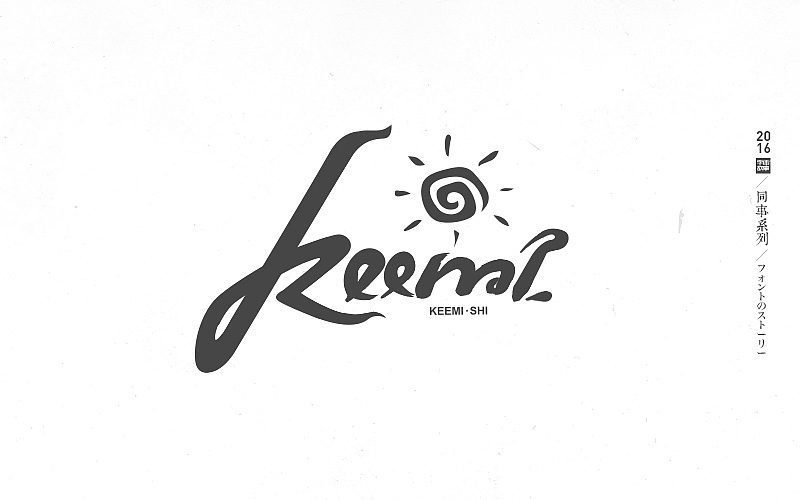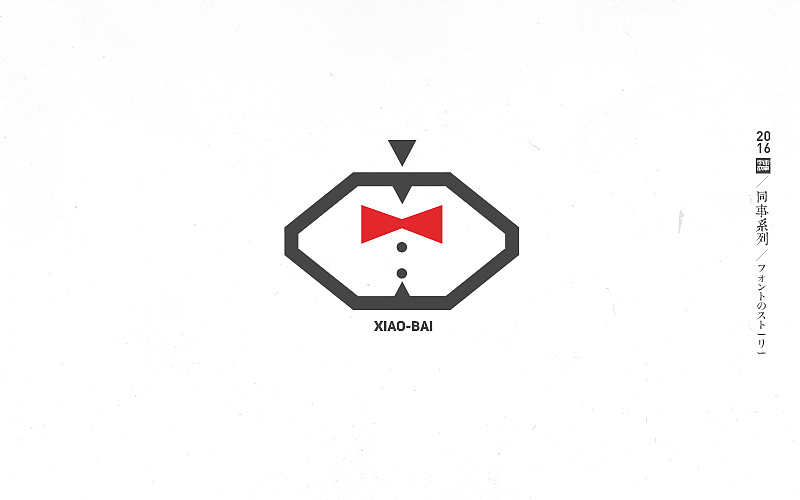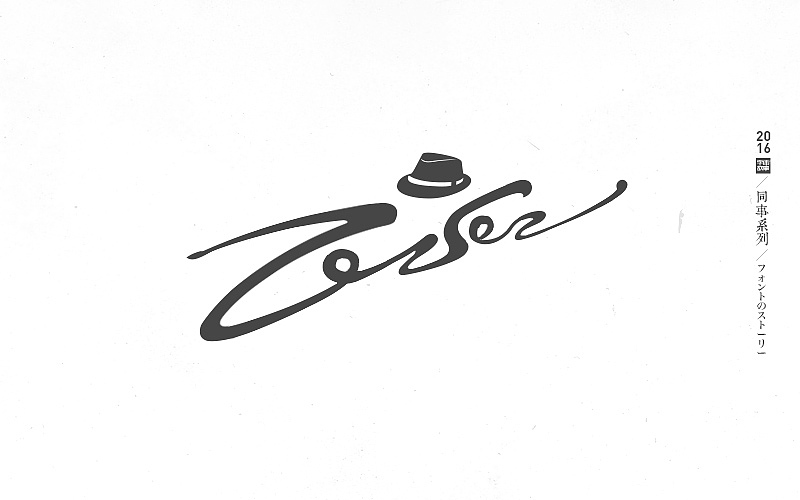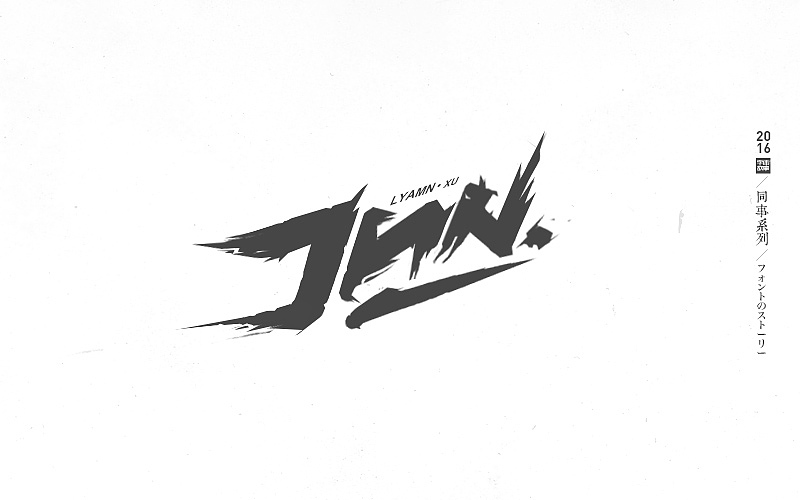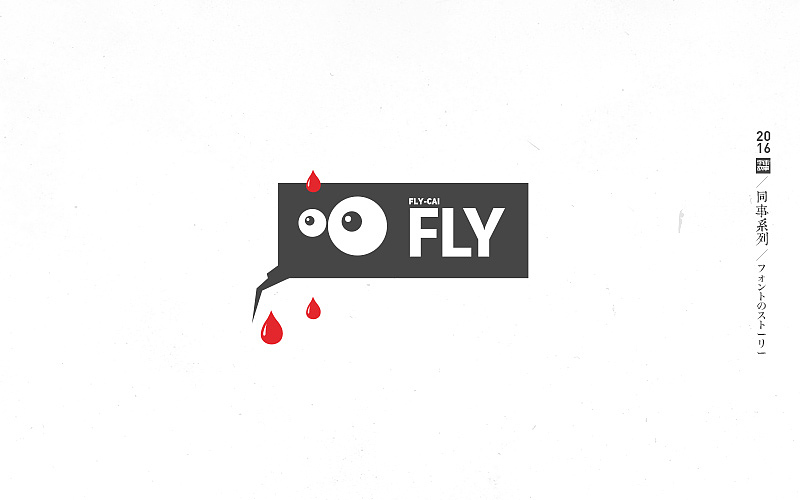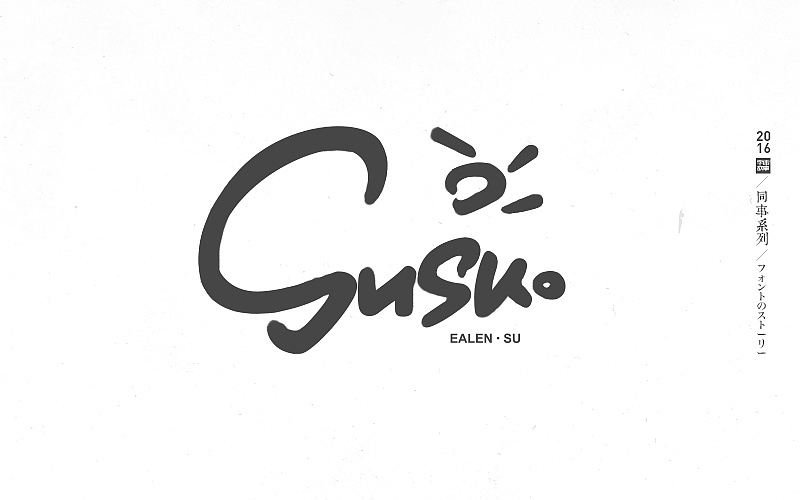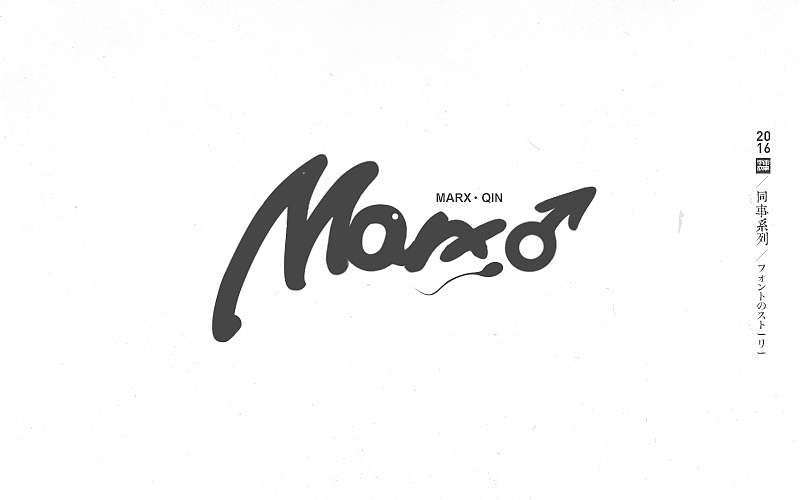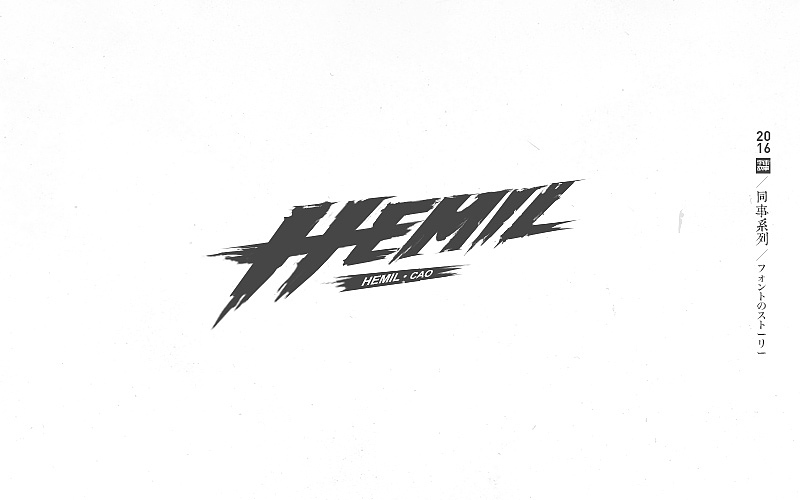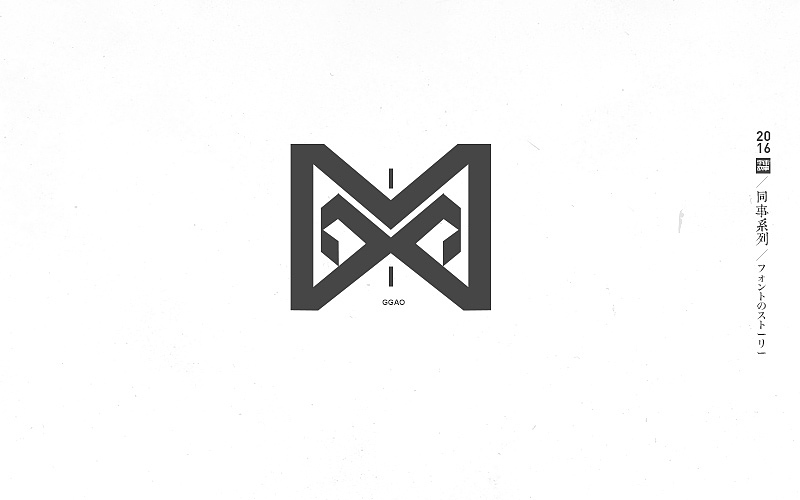
2016字体故事-同事名设计1
2016字体第一发!上半年一直在忙《字体故事》书的撰写还有工作项目攻坚,许久没发作品,《字体故事》10月份左右会面试,从字体属性和造字原理讲解字体设计。届时希望大家喜欢!
这里是老一组的同事们,包括上海和分离出去的同事们,本人自己根据昵称和RTX设计的,纯做字体练习和娱乐。
keemi,LOL启蒙老师,曾经在深圳(怀恋),后调去上海,阳光男孩,大帅哥,好爸爸!
小白,简直帅的一B!可惜结婚了,所以用了蝴蝶结,也是上海人,回上海家了!
box,狗富贵设计师,微信下载百万级,简直太屌,前海千万级业主!广州增城张少爷!
zesen,TG第一帅哥,喜欢带帽子,迷倒无数女生!
yuanyuan,腾讯第一美男,重庆人,单身!曾经在深圳,也去上海了!
junjun,上海同事,超级无敌奶爸!记得曾经的轩辕传奇嘛!逆天的设计!
FLY,低调型男!不好意思,你的英文我做成了苍蝇,但不会挡不住你的帅!
ellen,山东美女!从北京畅游过来的!声音很好听哦!不信听的试试?
ice,前御龙首席设计师!由于深圳房子太贵,去阿里了!平时AV达人,找什么女主角问他!单身,现在越来越有韩国藕霸气质了!
七爷,全能王!微单相机大人!引领了TG微单潮!无所不能,天下第一好男人!饭烧的一流,TG第一ADC!
jenny,时尚广西妹子!又叫兔子!对,比较瘦的兔子!
susu,福建帅哥痞子,口头弹“垃圾,菜B”!
miss,江湖人称小凉哥!90后美女,LOL钻石级玩家,设计做的炒鸡棒,烧菜也好吃,!
marx,肥牛大哥!阿里过来的员工,绘画达人!单身,雄性荷尔蒙比较旺盛!
ejin,小彦!不说了!《形式感+》的美女,书复印N版了,台湾繁体版刚买了版权!
米克,优质大米!钻石王老五!单身钻石男!
hemil,怪物猎人首席,健身达人!型男帅哥!
kaero,不好意思!这个也是七爷的!唯一做了2个的,这个比较蒙,七爷骨子里的性格!
kiwil,X姐!腾讯沙画第一人!离开我们了,要去美国深造了!5年后要记得我们,X姐!
ggao,高高不好意思,我记得你是开名爵的车。
高露J,没错,牙膏,是我!